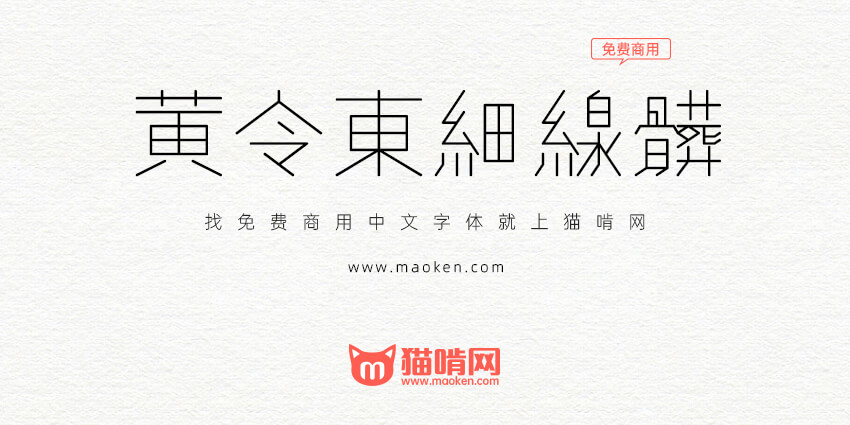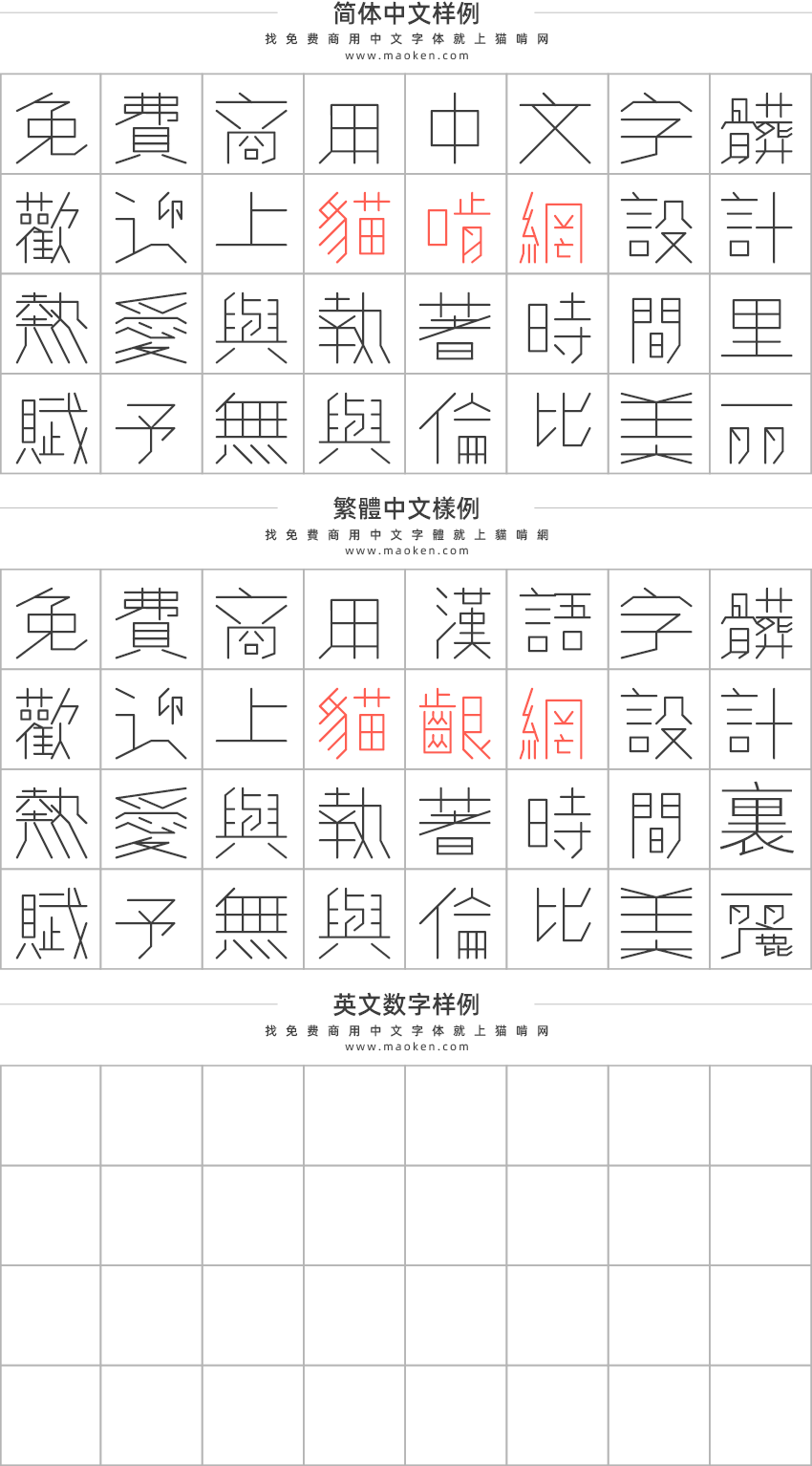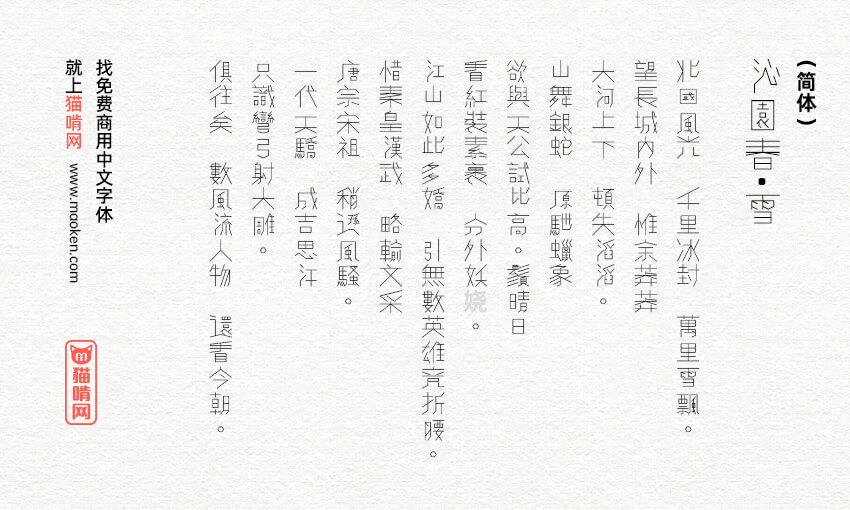
黄令东细线体:电脑程序自动生产的细线字体免费商用
字体作者:黄令东 (中国大陆) 字体字重:1个
黄令东细线体是一款十分特别的字体,这款字体是用程序自动生成,用递归根式包装语言(RRPL)进行编写。在RRPL中,每个汉字被描述为数字、符号和对其他字符的引用的短字符串。它的语法灵感来自标记语言,如乳胶,以及传统的用于书法练习的“米”网格。
目前黄令东细线体使用5000+的繁体汉字和词根,其字形由默认解析器生成。如有兴趣,可以点击这里去观看字体生成的演示程序。由于是程序自动生成的字体,所以难免会有错别字,大家使用时请检查清楚。
值得注意的是,这款字体是繁体的词根,输入简体字的话会直接映射成繁体字形。比如说你输入“汉”字,会被成繁体的“漢”字。
• 网友Alexander Misel修正了一些错别字。
这字体不错但就是没有简体字……希望能够把这个字符补一补吧……用心好好补不要用那些类似字体去补充来滥竽充数,要自己设计一个同样风格的字体的文字补充在简体等一些没有显示到的字体区域。
这个字体的样例“北国风光……”应该标注繁体,而不是简体。
BUG:「体」和「體」輸入的是「髒」!
• 呵呵,是的,程序自动生成的字体难免会有错别字。
• 我帮忙修复了,如果发现其他错字,也可通过类似方式提交修改。https://github.com/LingDong-/rrpl/pull/13
• 實例中「裏」居然是OppoSans,肯定是缺字了?
• 是缺字了,这里是个空白
• 确实比较无语,低级错误啊